シリーズ和文書体デザイン/コピペできない“木”
コピペできない“木”01「ハライとテン」
今回からは「木」だけに注目して、漢字制作でどのような調整をしているかの紹介です。「札杉村極機樹呆栄柴新欝…」など「木」が入っている漢字は非常に多く、しかし全ての「木」をコピー&ペーストして使いまわしでは文字として不自然なアウトラインになってしまうので、様々な調整をして一文字一文字に合わせていきます。
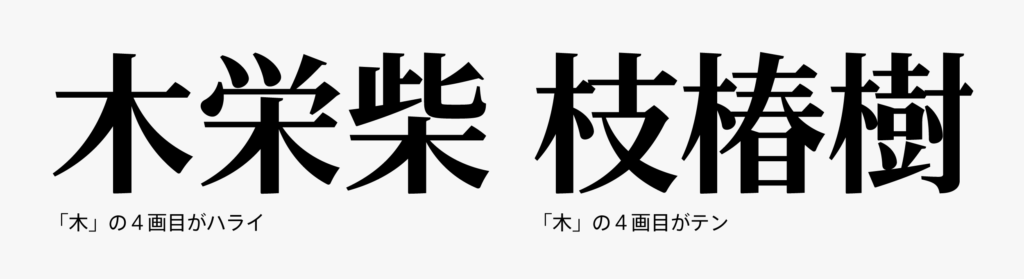
まず大きな変更点として、4画目をハライにするかテンにするかの2パターンがあります。旁(つくり)や足(あし)のように右側か中央に置かれる「木」は4画目をハライ、偏のように左側にある「木」は4画目をテンにする場合が多いです。ハライの場合は左右ハライを同じくらいの長さにする傾向があり、テンの場合は左ハライとはっきり長さを変えて短めにする、という特徴があります。「木」に近い形状の部首「禾米耒」などでもこの2パターンは共通です。